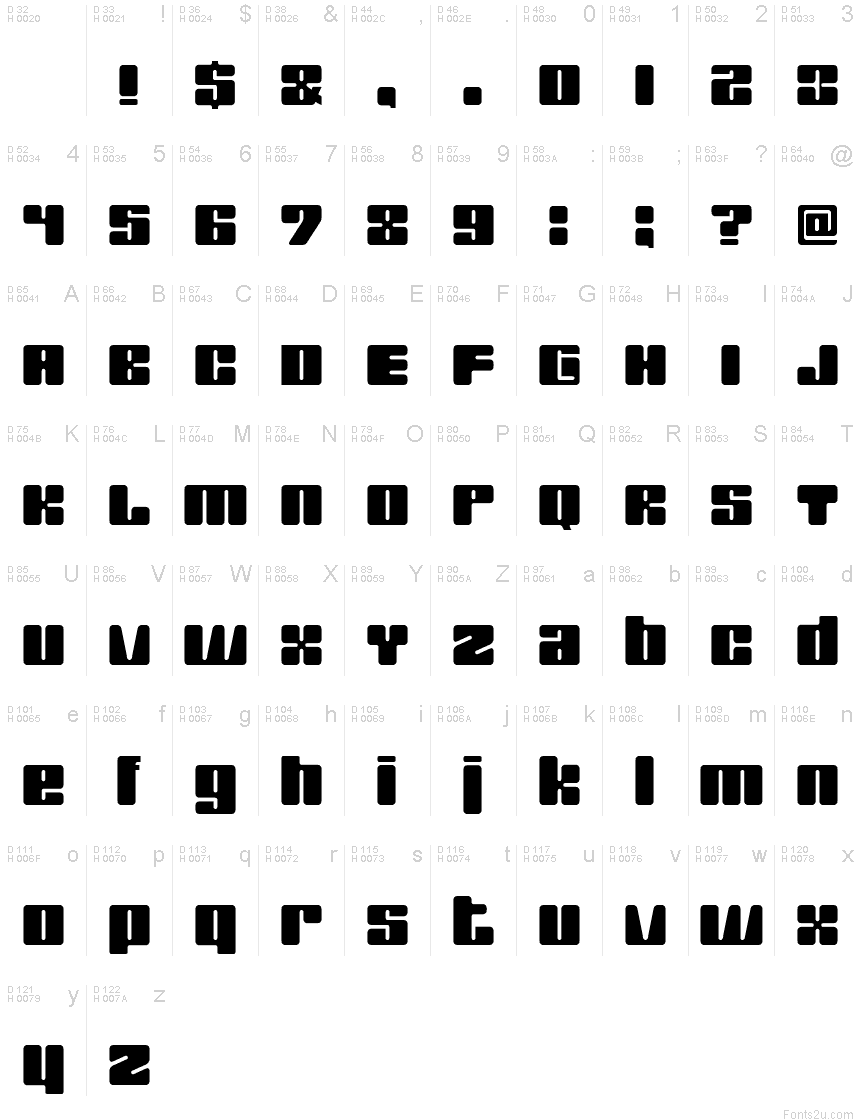
يعد Square Wise من LeFly خط عرض عصرياً ومجانياً بطابع تقني، يتميز بإيقاع يشبه تركيبات الألغاز. تبدو الحروف مضغوطة وهندسية، مع زوايا داخلية مستديرة وشقوق عميقة تجعل شكل الكلمة يبدو ككتل متداخلة بدلاً من الخطوط العادية بلا زوائد.
يناسب هذا الخط بشكل طبيعي رسومات الألعاب، ونشرات الأندية، وعناوين الملصقات، وشاشات تشغيل التطبيقات، وتصميم التغليف، حيث يحتاج العنوان المدمج إلى لمسة رقمية حادة. وباعتباره خطاً مجانياً، فهو مفيد بشكل خاص للشعارات، وعناوين الغلاف، والكلمات القصيرة، لأن الوصلات المقطوعة والمنحنيات المربعة تمنح حتى الكلمات القصيرة مظهراً متماسكاً وهيكلياً.